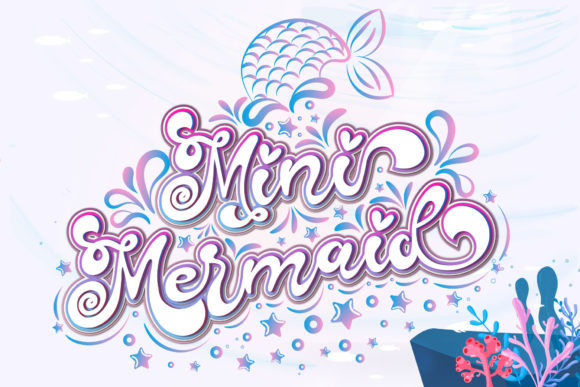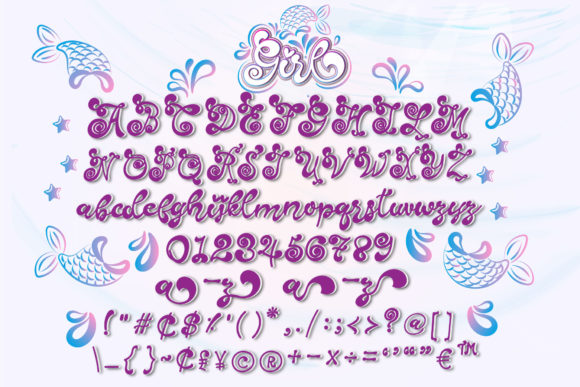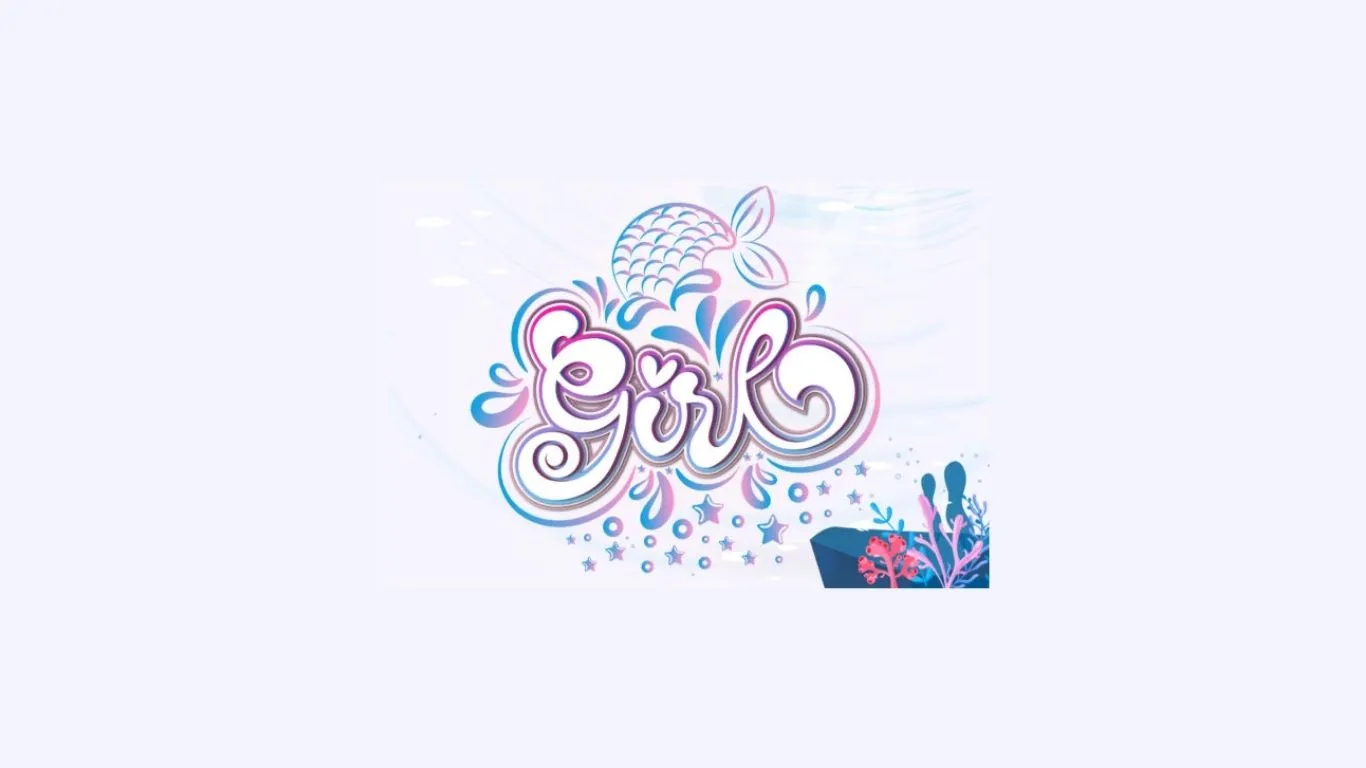
今天 Creative Fabrica 的限時免費字體是 Girl,原價 $18 美元,現在限時 24 小時免費下載,還附帶商業授權。字體融合了美人魚裝飾符號,支援 PUA 編碼,因此可以輕鬆取用所有花式字符 (Swashes) 與裝飾細節。
Girl 是由設計師 Nobu Collections 製作的雙字型套裝,在 Creative Fabrica 上已累計超過 2833 人收藏,並獲得 16 則評價、滿分 5 星。